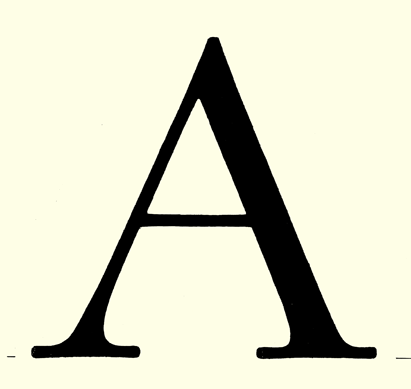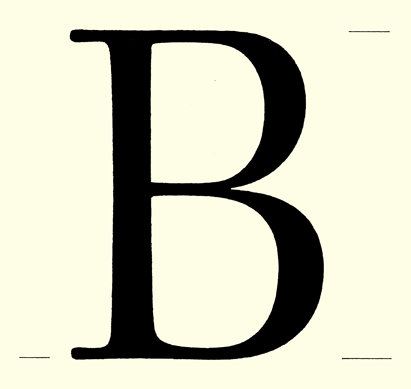
![]() | Michael Harvey (1931–2013) werkte als technisch tekenaar toen hij de autobiografie van Eric Gill in handen kreeg. Dit boek inspireerde hem om letters in steen te gaan hakken. Van 1955 tot 1961 was hij assistent van Reynolds Stone en maakte hij inscripties in allerlei soorten steen en hout. Harvey heeft vele beletteringen gemaakt, waaronder gedenkstenen in verschillende kathedralen, en de steen ter gelegenheid van de voltooiing van de restauratie van Windsor Castle. In 1990 beletterde hij de grote fries van de Sainsbury-vleugel, de door Robert Venturi ontworpen uitbreiding van de National Gallery aan Trafalgar Square. Michael Harvey was een Member of the Order of the British Empire. | |||||||||||||||||